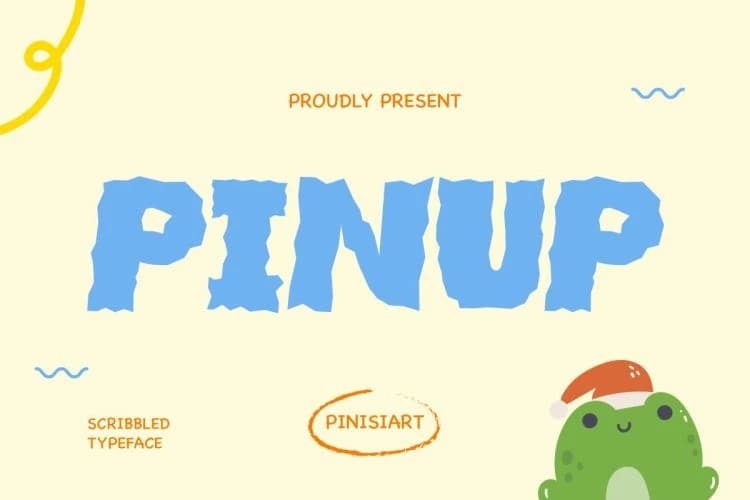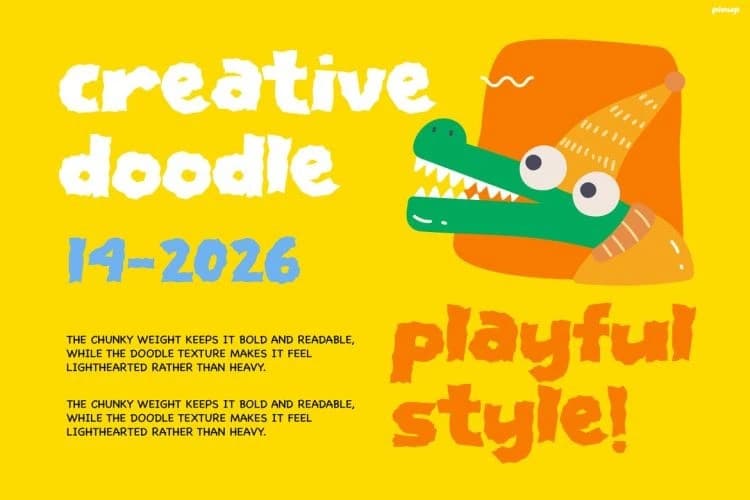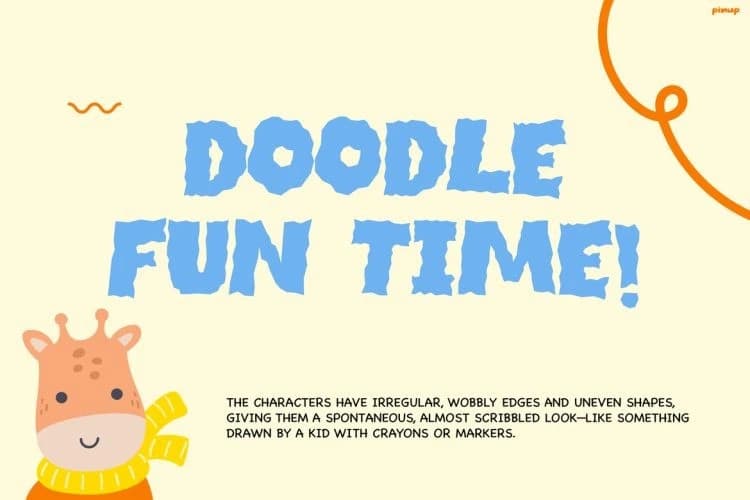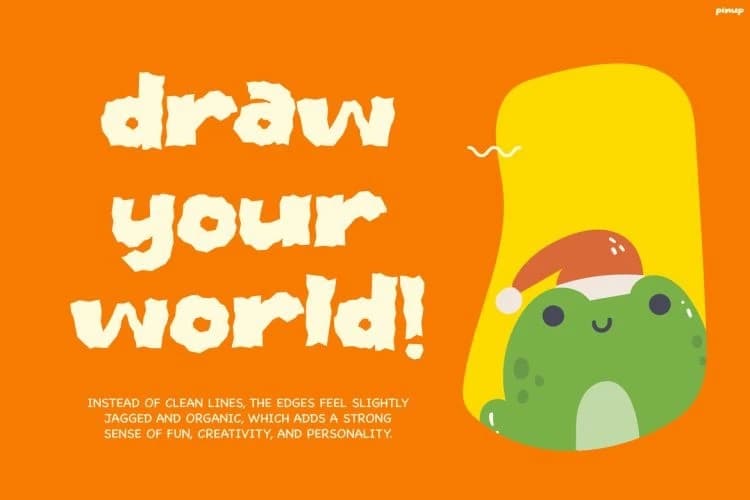
Pinup Display Font
Pinup Display Font neşeli bir enerjiyle dolup taşar; kalın el çizimi şekiller ve yumuşak düzensiz kenarların birleşimi canlı ve ifade dolu bir his verir. Cesur, köpüklü stili anında dikkat çekerken, kusurlu çizgiler doğal, doodle benzeri bir çekicilik katar.
Pinup Display Font neşeli bir enerjiyle patlar, kalın elle çizilmiş şekiller ve yumuşak düzensiz kenarları bir araya getirerek canlı ve ifade dolu bir hava yaratır. Kalın ve neşeli stili hemen dikkat çeker; kusurlu çizgiler doğal, karalama benzeri bir çekicilik katar.
Pinup Display